Font chữ con dấu là gì và đặc trưng trong nhận diện pháp lý?
Font chữ con dấu là những bộ phông được thiết kế theo quy chuẩn hình học nghiêm ngặt để phục vụ việc tạo ra các loại con dấu hành chính hoặc dấu chức danh. Đặc trưng của dòng font chữ làm con dấu là nét chữ vững chãi, rõ ràng và có sự cân đối tuyệt vời về bố cục. Trong các văn bản hành chính, font chữ con dấu tròn hay font chữ con dấu vuông đóng vai trò là bảo chứng cho uy tín và giá trị xác thực của thực thể kinh tế.
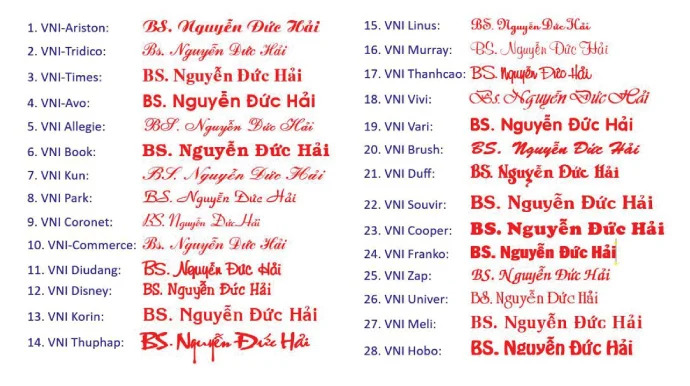
05 Ứng dụng phổ biến của font chữ làm con dấu trong thực tế
Vẻ đẹp trang trọng và tính chuẩn xác của các mẫu chữ con dấu nâng tầm giá trị cho nhiều ấn phẩm truyền thông của đơn vị:
- Khắc dấu tròn và dấu vuông doanh nghiệp: Font chữ khắc dấu tròn là thành phần cốt lõi để tạo nên con dấu pháp nhân. Độ sắc sảo của phông chữ giúp mộc dấu sau khi đóng lên giấy tờ luôn rõ nét, dễ nhận diện và khó làm giả.
- Sản xuất mộc tên và chức danh cá nhân: Sử dụng font chữ khắc dấu tên để làm con dấu cá nhân cho lãnh đạo hoặc nhân viên. Những nét chữ rõ ràng giúp việc đóng dấu trên các tập hồ sơ hay bao thư trở nên nhanh chóng và chuyên nghiệp.
- Thiết kế bao bì túi giấy đựng tài liệu: Hình ảnh font con dấu cách điệu thường được in trên túi giấy Ivory hay Kraft của các công ty luật, tài chính. Điều này tạo cảm giác tin cậy và minh bạch đối với khách hàng sử dụng dịch vụ.
- Gia công in UV trên các hiện vật lưu niệm: Logo lồng ghép cùng kiểu chữ con dấu được in trên bình giữ nhiệt kim loại hoặc sổ tay da. Công nghệ in tại In Viva giúp các đường nét hình học hiển thị sắc sảo, bền màu theo thời gian.
- Trang trí voucher và thẻ đặc quyền VIP: Một biểu tượng hình dấu mộc dùng font chữ đóng dấu trên thẻ tri ân giúp tạo điểm nhấn độc đáo, gợi nhắc về sự cam kết uy tín của nhãn hàng đối với người sở hữu.
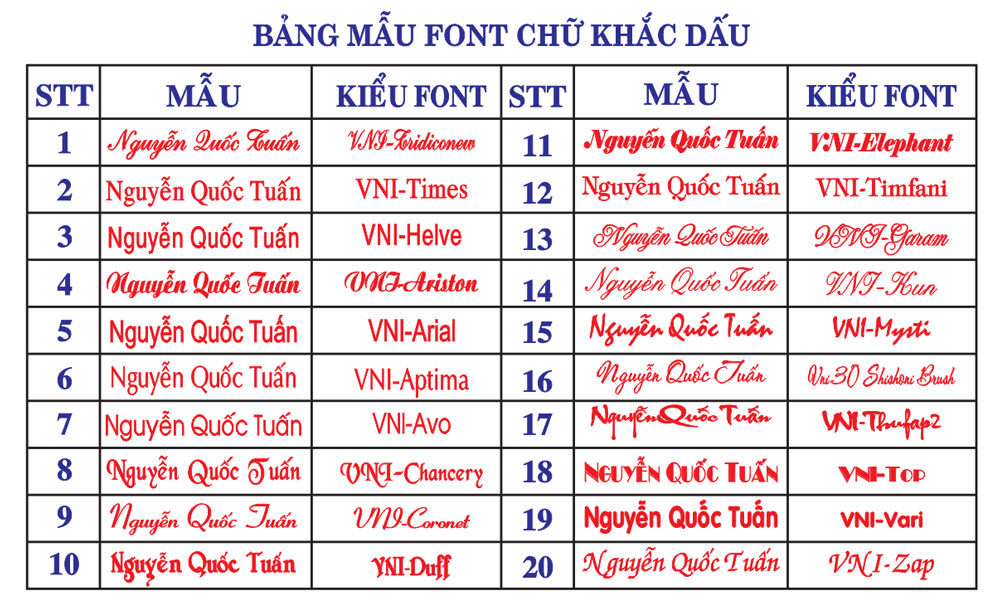
04 Lưu ý kỹ thuật khi sử dụng font chữ khắc dấu tròn in ấn
Để hệ thống ký tự hiển thị sống động và bền màu trên các thành phẩm thực tế như giấy mỹ thuật hay bề mặt cứng, designer cần chú trọng:
- Kiểm soát độ dày nét chữ (Stroke): Font chữ con dấu tên thường có nét chữ thanh mảnh. Designer nên điều chỉnh độ dày vừa đủ để khi khắc laser hoặc in lụa, mực bám ổn định, tránh tình trạng chữ bị đứt đoạn hay mờ nhòe.
- Tối ưu đường Path for gia công bế nổi: Bước này đặc biệt quan trọng khi sản xuất nắp hộp cứng dập nổi logo hình dấu mộc. Kỹ thuật viên cần làm mượt các điểm neo tròn trong file vector giúp khuôn bế thực hiện chính xác, tạo hiệu ứng nổi khối rạng rỡ cho các chi tiết uốn lượn.
- Thiết lập hệ màu CMYK chuẩn: Với các con dấu màu đỏ chu sa đặc trưng, bạn cần hiệu chỉnh hệ màu CMYK chuẩn in ấn tại xưởng và yêu cầu mẫu thử để đảm bảo màu chữ sau in rực rỡ và chân thực.
- Đảm bảo tính chính xác của bảng mã: Khi sử dụng font chữ con dấu, hãy luôn thực hiện lệnh Create Outlines trước khi bàn giao file cho xưởng in công nghiệp để loại bỏ rủi ro bị nhảy font ngoài ý muốn trên các hệ máy khác nhau.